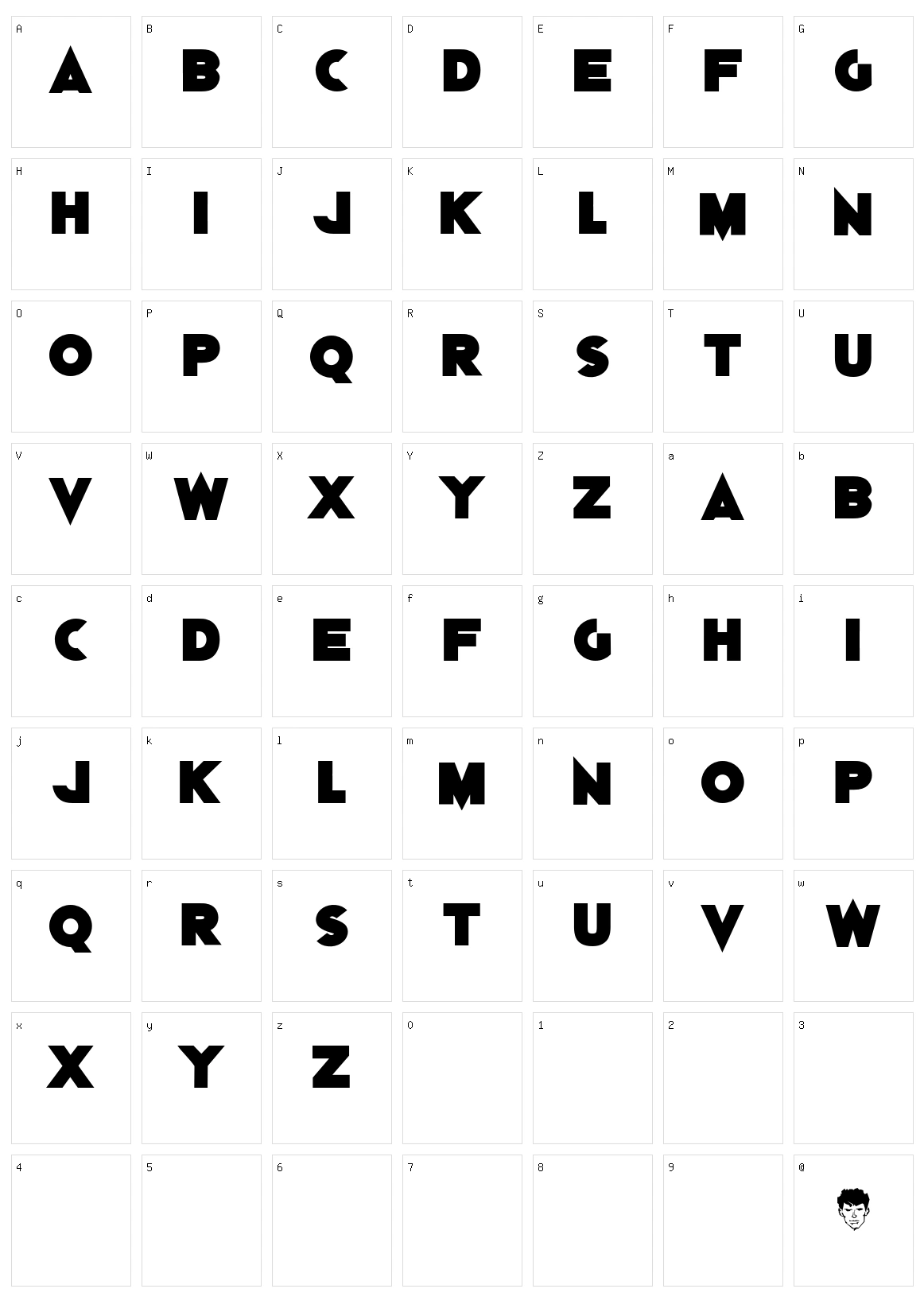
Font name: DYLAN DOG Font (FontCOMICS Collection) - Latin Decorative font (versione 1.0)
Type designer: P. A. Vannucci
DYLAN DOG font: direttamente dal film diretto da KEVIN MUNROE e interpretato da BRANDON ROUTH, il font inedito per tutti
gli estimatori del film. Da notare il ritocco necessario in Photoshop per conferire, alla titolazione, l'originale bordatura.
DYLAN DOG font: directly from the Best movie by KEVIN MUNROE, with BRANDON ROUTH,
the original font for all lovers. Use ADOBE Photoshop for the original border from title.